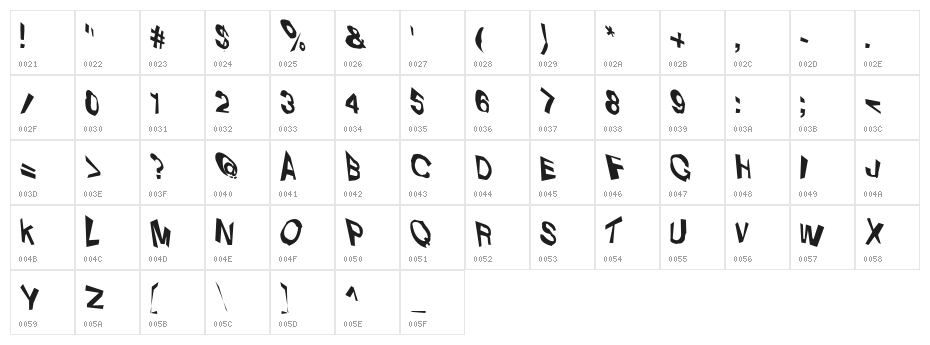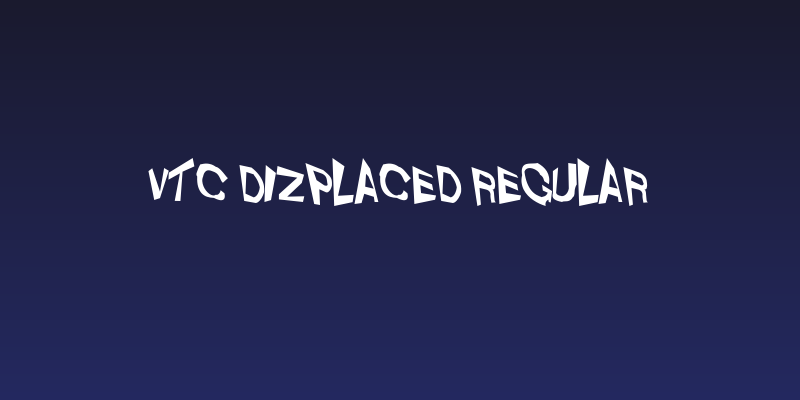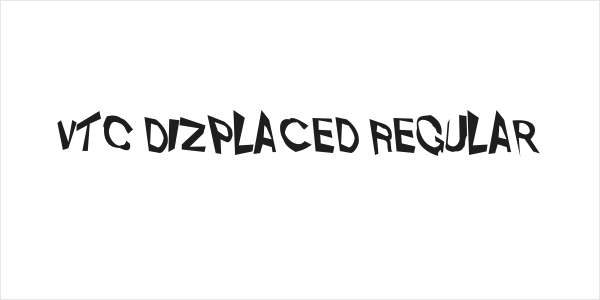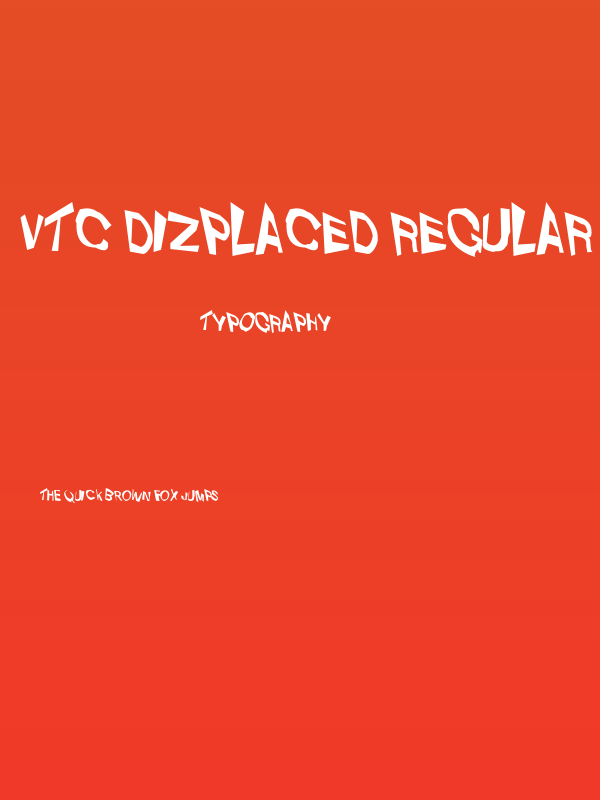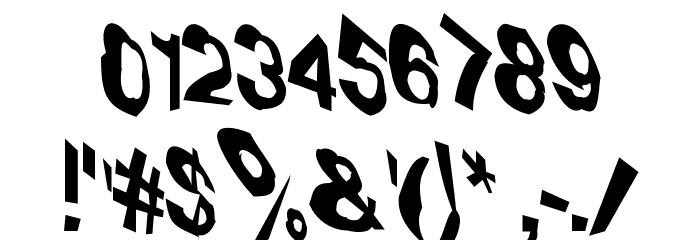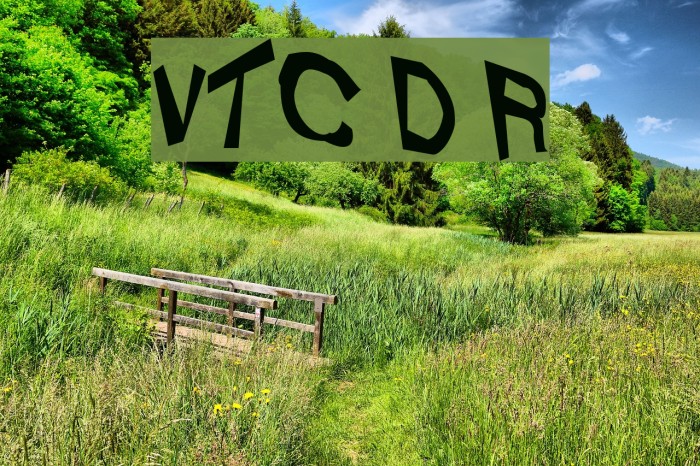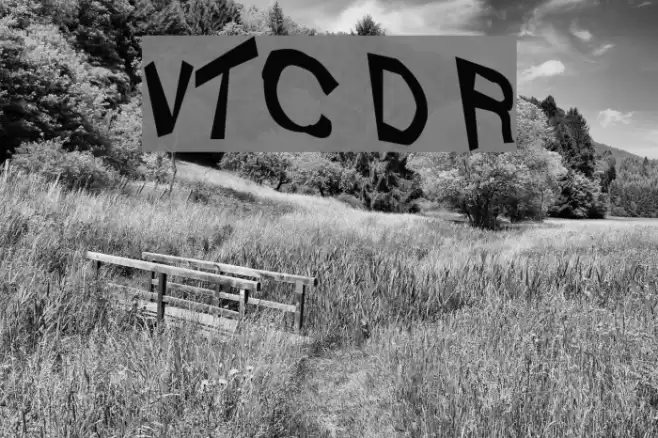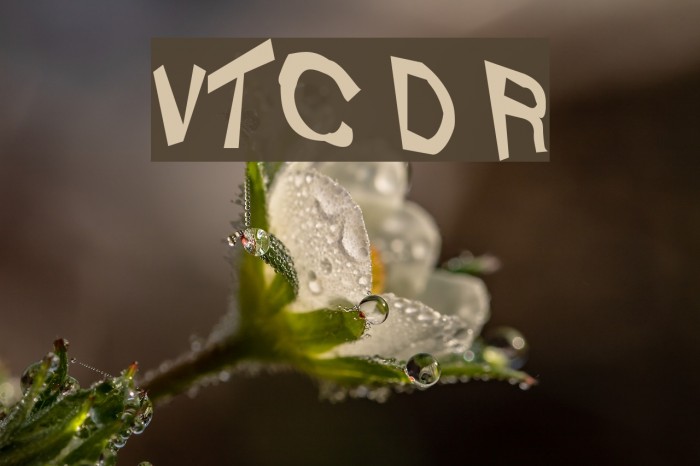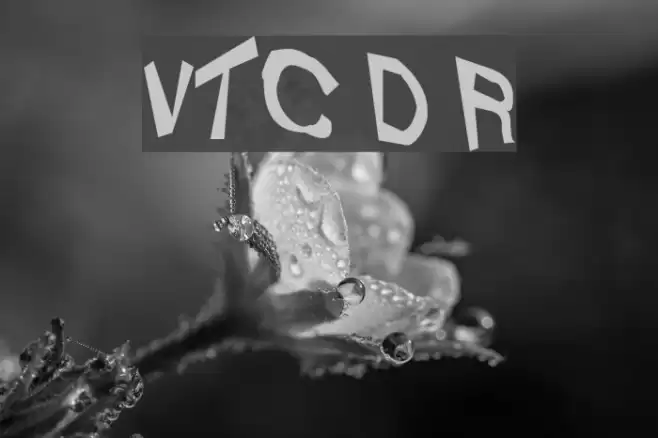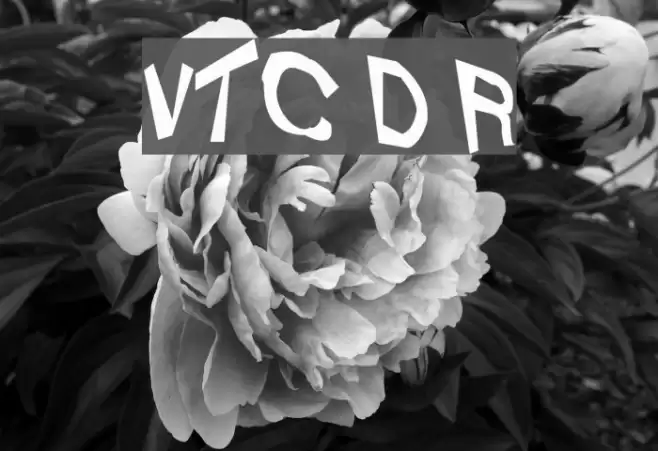
VTC Dizplaced Regular Font
| Vorgeschlagene Projekte | Ideal for posters, album covers, children's books, or any project needing a bold and quirky aesthetic. |